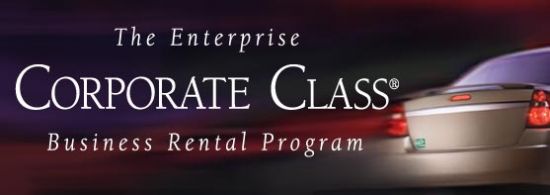
Schrift Autovermietung
kennt Einer von Euch diese Schrift? Ich dachte zuerst an die ITC Weidemann, aber die ist es wohl nicht ... BTW: Heißt es nicht, dass wer Minuskeln spationiert, auch Schafe f***?
Und wer Versalien/Kapitälchen so eng setzt ist ein ganz schlimmer...
Schrift kenne ich leider auch nicht.
Markant: Die Spitze des "A", die in die "falsche" Richtung zeigt.
Und wer Versalien/Kapitälchen so eng setzt ist ein ganz schlimmer...